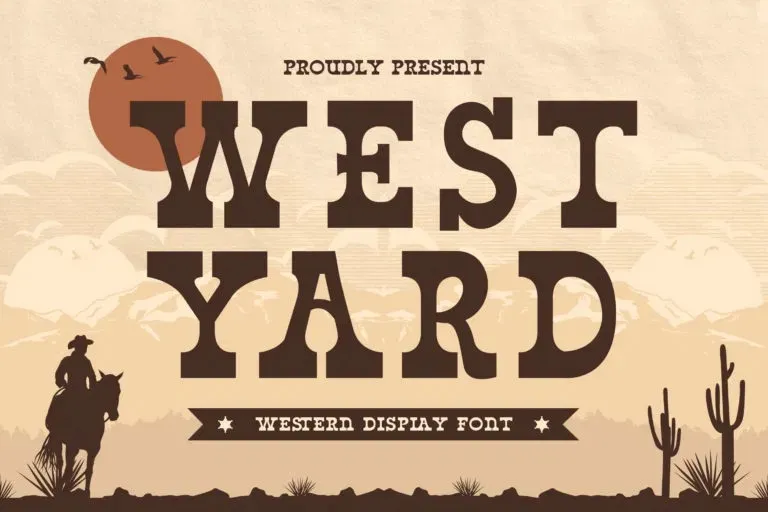
West Yard Font – Fonte Grátis
West Yard Font
Esta fonte tipo é inspirada nos antigos tipos de letra com estilos retro combinados com nuances decorativas do estilo Slab que remetem ao período dos anos 70 e 80, quando os traços mais robustos se tornaram populares novamente. Seja para design de histórias em quadrinhos, jogos infantis, citações, títulos de filmes, nomes de marcas, capas de livros ou até mesmo qualquer criação que precise de um toque delicado e sofisticado, esta fonte é uma escolha excepcional. Ela traz um ar elegante ao seu trabalho sem perder sua personalidade única, adequada para diversos usos em designs digitais.